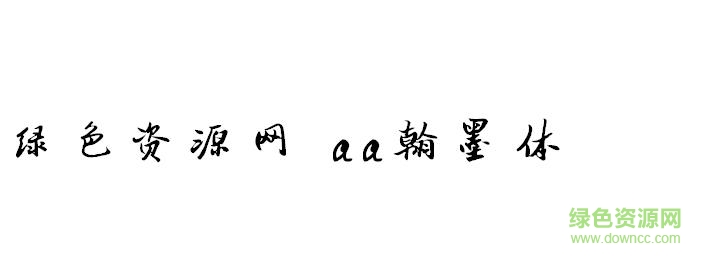
翰墨體字體
Aa翰墨體ttf擁有十分濃厚的文學(xué)氣息,讓你在使用的時(shí)候能夠感受到古代的字體韻味,仿佛置身翰林院一般使用這款自己進(jìn)行書(shū)寫(xiě),通過(guò)使用這款字體進(jìn)行閱讀也將獲得不錯(cuò)感受,快來(lái)綠色資源網(wǎng)下載吧!
aa翰墨體ttf字體介紹
aa翰墨體ttf